フォントの選定は、デザインの印象や読みやすさなどを左右する重要な役割を担っています。しかし、種類が多すぎて探すのにも一苦労ではないでしょうか。
フォント選定のコツ
ここではフォント選定やフォントの特徴について触れていきます。
フォントについて
フォントの特徴まとめ
明朝体の特徴(日本語フォント)
- 細線と太線で構成されている
- 右肩に三角の装飾(ウロコ)がある
- 長時間読んでいても疲れにくいため本文に向いている
- 太字が並んでしまうと読みにくさを与えるので注意
- 太字に設定すること視認性が高まるため見出し向き
- 細字の印象…ふんわり、洗礼された、上品、高級感、女性的
- 太字の印象…優雅、歴史的、権威的
ゴシック体の特徴(日本語フォント)
- フォントの太さがほぼ均一
- ウロコは(ほぼ)ない
- カジュアルで親近感のあるデザイン
- 太字に設定すること視認性が高まるため見出し向き
- フォント自体の印象…安定感、信頼感、男性的
- 太字の印象…力強さ、インパクト
- 丸ゴシックの印象…かわいらしさ、若さ、親しみ
筆書体の特徴(日本語フォント)
- 毛筆で書いたようなデザイン
- 細字の印象…和、伝統的
- 太字の印象…力強さ、インパクト
デザイン体の特徴(日本語フォント)
- 手書き風、POP、特徴的な書体はデザイン体に属する
- 装飾向き
- 印象はフォントによって異なります
セリフ体(欧文フォント)
- 日本語フォントでは明朝体のような位置
- 細線と太線で構成されている
- 文字の一部に細線や三角、四角形の装飾(セリフ)がある
- 本文向き
- 太字に設定すること視認性が高まるため見出し向き
- フォント自体の印象…ふんわり、洗礼された、上品、高級感、女性的
サンセリフ体(欧文フォント)
- 日本語フォントではゴシック体のような位置
- 欧文書体の中でもセリフがないもの
- 細字であればシンプルで見やすい
- 太字に設定すること視認性が高まるため見出し向き
- フォント自体の印象…安定感、信頼感、男性的
- 太字の印象…力強さ、インパクト
スクリプト体(欧文フォント)
- 手書き風、筆記体が含まれる
- 装飾向き
- 印象はフォントによって異なります
読みやすいフォント一覧
ZEN 角ゴシックNEW シリーズ
ZEN 角ゴシックNEW Regular
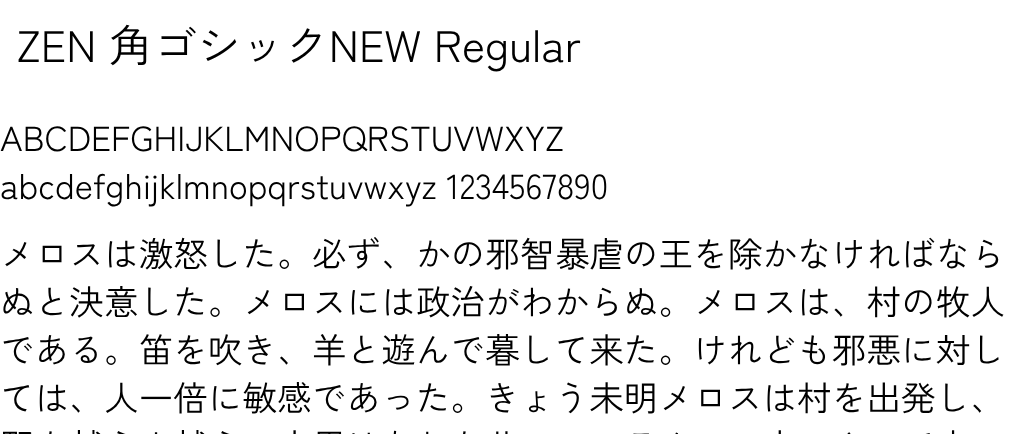
ZEN 角ゴシックNEW Medium
- 角ゴシック
IPAex明朝
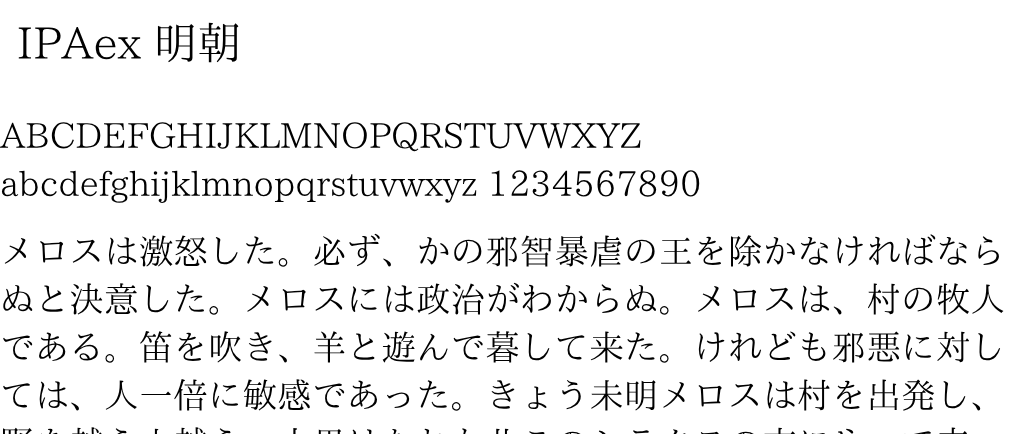
- 明朝体
マメロン
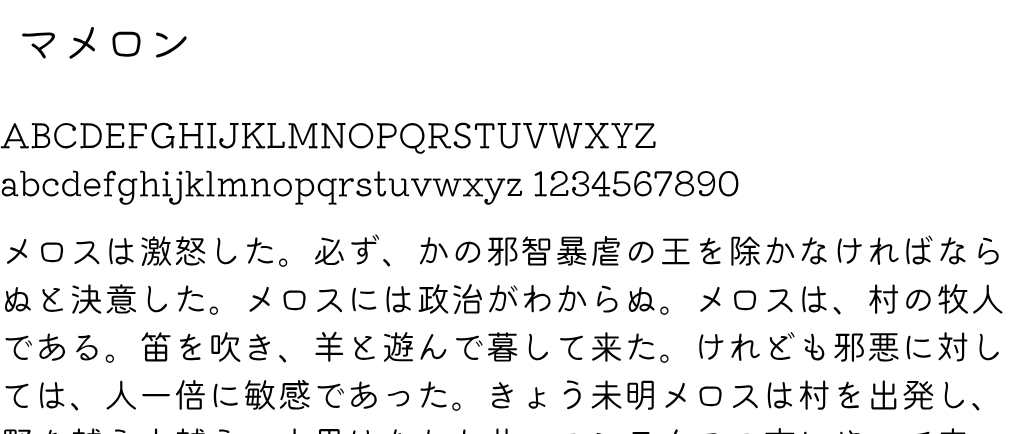
- 丸ゴシック
Noto Sans
- 人気のゴシック体
モボ
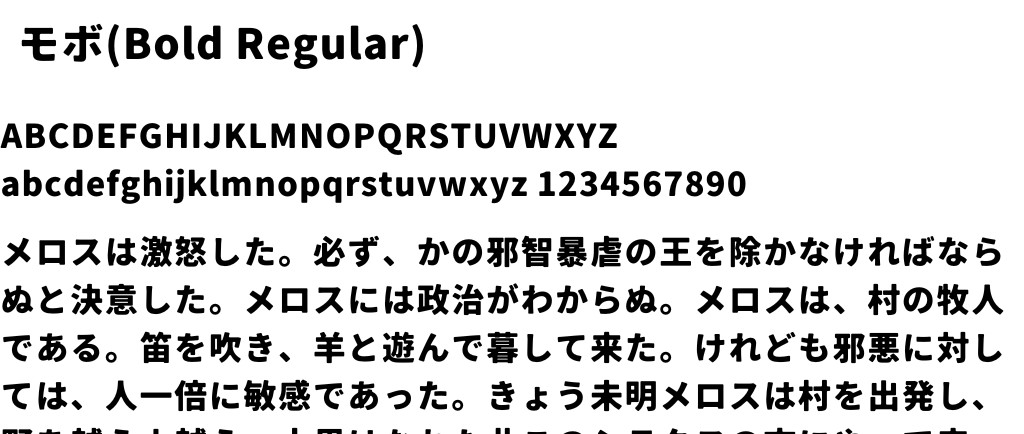
- フリーフォント/商用利用可
- 角ゴシック
つなぎゴシック
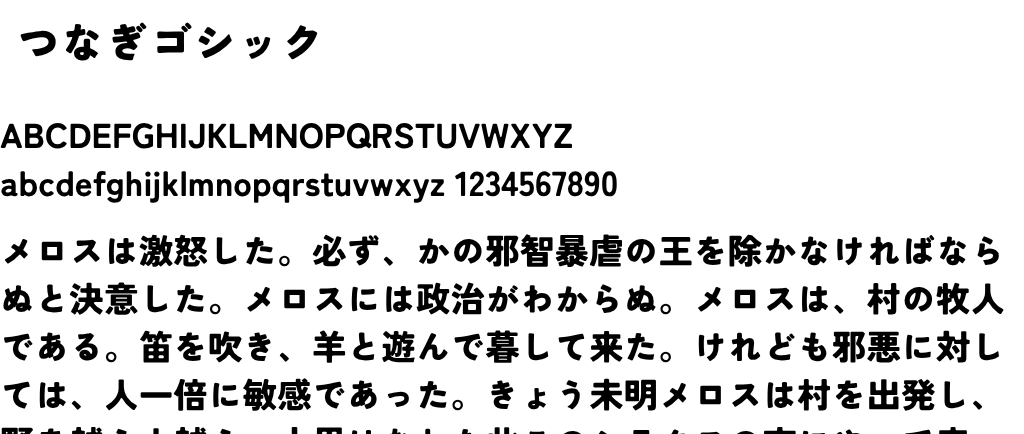
- フリーフォント/商用利用可
- Zen角ゴシックNがベース
セザンヌシリーズ
ニューセザンヌ(N仕様)
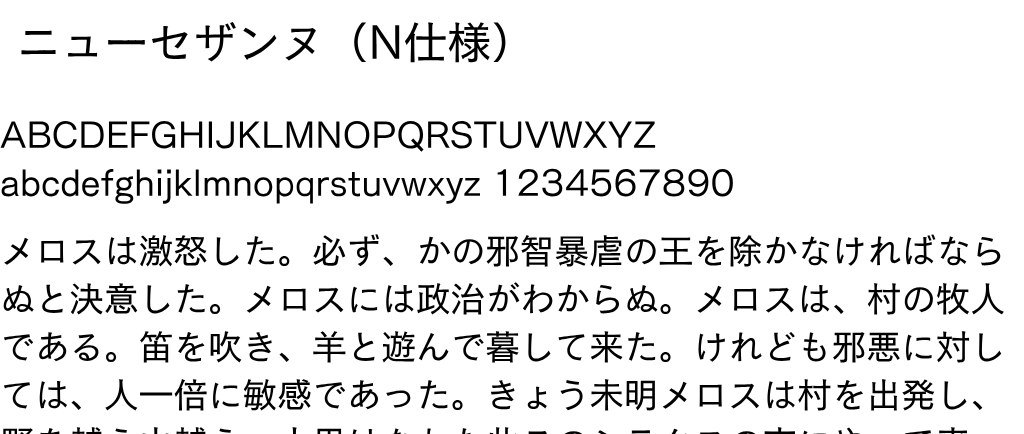
セザンヌ
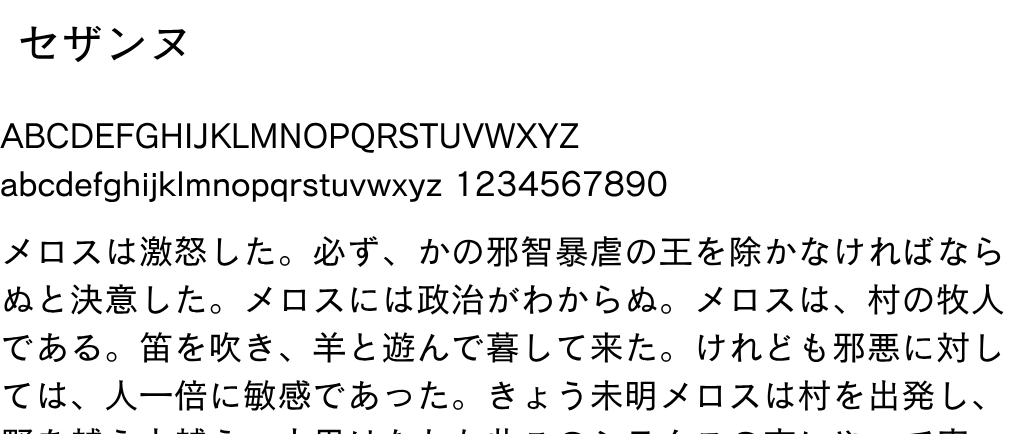
セザンヌDB
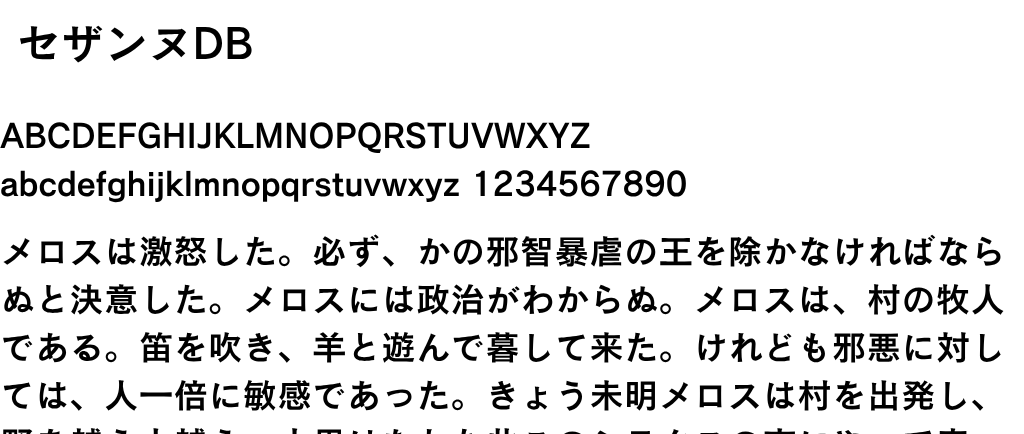
アンチックセザンヌ
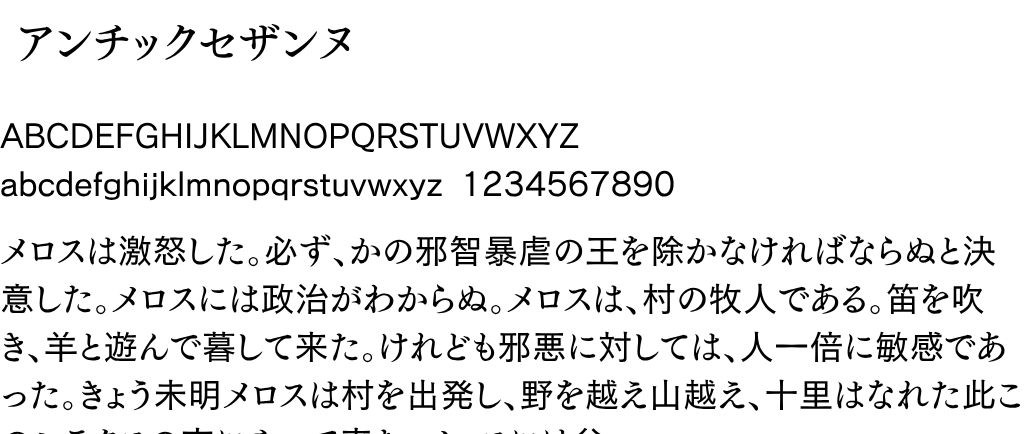
- 人気の角ゴシック
Montserrat
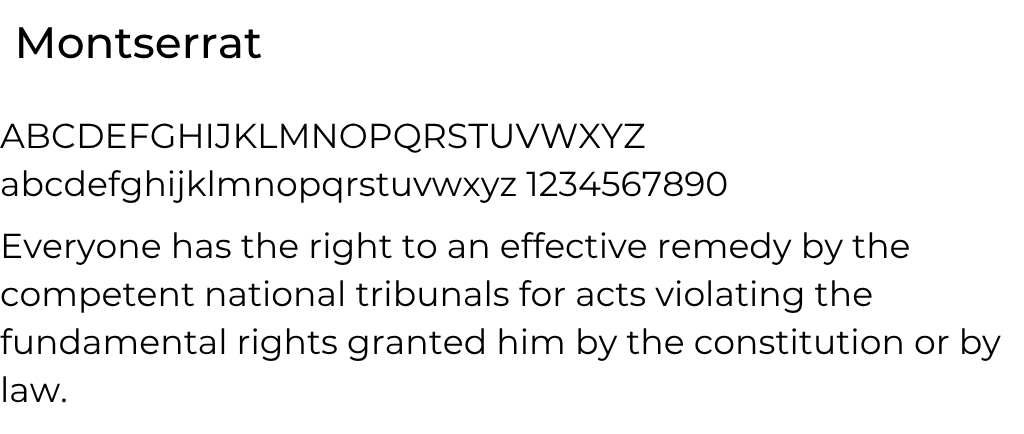
- フリーフォント/商用利用可
- 英字のみ
- サンセリフ体
KIONA
- フリーフォント/商用利用可
- 英字(大文字)のみ
- サンセリフ体
Rounded M+ 1p
- フリーフォント/商用利用可
- ゴシック体
Kiwi Maru
- フリーフォント/商用利用可
- Google フォント
- セリフ体
Kosugi Maru
- フリーフォント/商用利用可
- サンセリフ体
LINE Seed シリーズ
LINE Seed JP Regular
LINE Seed JP Thin
LINE Seed JP Bold
LINE Seed JP ExtraBold
- フリーフォント/商用利用可
- LINE フォント
高級感のあるフォント一覧
うつくし明朝体オールド
- フリーフォント/商用利用可
- 明朝体
- レトロ・やわらかい
はれのそら明朝
- フリーフォント/商用利用可
- 明朝体
はんなり明朝
- フリーフォント/商用利用可
- 明朝体
- 優しくふんわりした印象
ほのか明朝
- フリーフォント/商用利用可
- 明朝体
CINZEL
- フリーフォント/商用利用可
- 高級感
Casanova Serif Display Font
- フリーフォント/※個人利用
- 手書き
デザイン性の強いフォント一覧
ビルの谷間と高架下
- フリーフォント/商用利用可
- ※画像はフリー版
かんじゅくフォント
- フリーフォント/商用利用可
- 漢字以外はオリジナル/漢字をIPAexゴシックを改良したフォント
プラネタリウム
- フリーフォント/商用利用可
- 装飾
Kaisei Tokumin
- フリーフォント/商用利用可
- Google フォント
- きれいでデザイン性のある
Tsukimi Rounded
- フリーフォント/商用利用可
- Google フォント
- ひらがなとカタカナのみ
- 漢字を合わせるなら「ZEN丸ゴシック」「つぐみ丸ゴシック」がおすすめ
にくまる
- フリーフォント/商用利用可
- かわいい/ぷっくりとした丸ゴシックが特徴
こはるいろサンレイ
- フリーフォント/商用利用可
- レトロ調
ラノベPOP
- フリーフォント/商用利用可
- YouTubeでもテロップとしてよく見られるフォントの一種
けいふぉんと
- フリーフォント/商用利用可
- YouTubeでもテロップとしてよく見られるフォントの一種
吐き溜
- フリーフォント/商用利用可
- ホラー
Rampart One
- フリーフォント/商用利用可
- Google フォント
どきどきファンタジア
画像引用:BOOTH様(http://modi.jpn.org/font_memoir.php)
- フリーフォント/商用利用可
- ひらがな、カタカナのみ
- かわいらしい/POP/ツヤ
- Zen丸ゴシックの派生フォント
零ゴシック
画像引用:BOOTH様(http://modi.jpn.org/font_memoir.php)
- フリーフォント/商用利用可
- 源ノ角ゴシックを元にした派生フォント
瀞ノグリッチ黒体・瀞ノグリッチ明朝
- フリーフォント/商用利用可
- 源ノ角ゴシックを元にした派生フォント
めもわーる
- フリーフォント/商用利用可
- ひらがな向け
- ファンシーなレトロポップ調
- かわいい/メルヘン/夢系にもおすすめ
Cherry Bomb
- フリーフォント/商用利用可
- 漢字×
- ファンシー/かわいい/メルヘン/夢系にも◎
Little Devil
- フリーフォント/商用利用可
- 大文字アルファベット
- ホラー、ハロウィンデザインにも◎
手書きフォント一覧
- フリーフォント/商用利用可
- 「つきみ丸ゴかな」と「Zen丸ゴシック」を合成したフォント
- 手書き風
- フリーフォント/商用利用可
- すらすら流れるような筆致の字
- フリーフォント/商用利用可
- 源ノ明朝や源ノ角ゴシック、M+FONTをなぞって作ったフォント
クレー
- フリーフォント/商用利用可
- 鉛筆で書いたような手書き感
花鳥風月
- フリーフォント/商用利用可
- 明朝体
- ボールペンで書いたような手書き感
タイムマシンわ号
- フリーフォント/商用利用可
- 明朝体
- はんなりとした細丸行書
Zen Kurenaido
- フリーフォント/商用利用可
- 手書き
無心
- フリーフォント/商用利用可
- 手書き
仕事メモ書きフォント/遊びメモ書きフォント
- フリーフォント/商用利用可
- 女の子らしい可愛い手書き文字
左利きの彼女
左利きの彼女(無料)※小3までの漢字を収録
左利きの彼女(有料)※有料版¥1,000
- フリーフォント/商用利用可
Nerko One
- フリーフォント/商用利用可
- 可愛い手書き文字
筆記体フォント一覧
Clicker Script
- フリーフォント/商用利用可
- 上品な筆記体/手書き
- ハロウィンデザインにも使えそう
Brittany
- フリーフォント/商用利用可
- 手書き
Debby Free Font
- フリーフォント/商用利用可
- 招待状にもおすすめ
- 手書き
Selfiana Tre Script Font
- フリーフォント/商用利用可
- 手書き
Joseph Sophia Script Font
- フリーフォント/商用利用可
- 手書き
Beloved Mother Calligraphy Font
- フリーフォント/商用利用可
- 手書き
- 高級感、おしゃれ、装飾にも
Luna – Free Font
- フリーフォント/商用利用可
- 手書き
- 子どものような字にも
Malaga Modern Script Free Typeface
- フリーフォント/商用利用可
- 手書き
- マーカー風
その他
装甲明朝
- フリーフォント/商用利用可
- 明朝体
万能フォント一覧
游ゴシック体
- 有料フォント
- 丸ゴシック
- Adobeフォント
Helveica
- macOS標準搭載/Windowsの方はこちら
- 世界中の駅などでも利用されているオーソドックスな欧文フォント
- Helveica Neueは「Helveica」の改良版
Acumin
- Helveicaの代用フォントにも◎
- Adobeフォント
筑紫シリーズ
- 有料フォント
- 筑紫A丸ゴシック Std R/BはAdobeフォント
モトヤシリーズ
- 有料フォント
- さまざまなパターンがあり汎用性が高い
まとめ
今回は「フォント選定のコツやフォントの特徴、さまざまな用途に合うフォント」について等をご紹介しました。
ビジネスシーンやトンマナによって合うフォントはさまざまですので、フォントをお探しの方は、ぜひ今回ご紹介したフォントをチェックしてみてください。